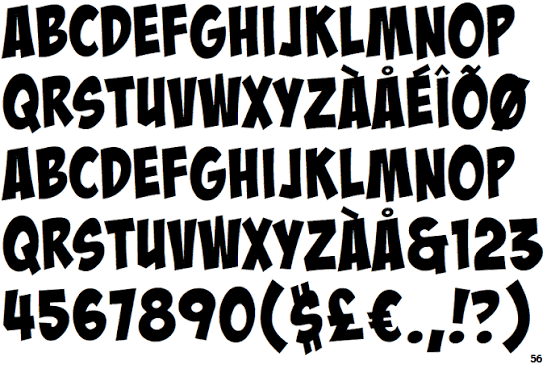
Sở hữu bộ phông chữ Badaboom chuẩn giúp các nhà thiết kế dễ dàng tạo dựng hình ảnh thương hiệu vui tươi, năng động và đầy sức hút. Toàn bộ dữ liệu tại In Viva đã được kiểm soát kỹ thuật kỹ lưỡng, đảm bảo tương thích hoàn hảo với các phần mềm đồ họa chuyên nghiệp hiện nay:
Ký tự đã được rã vector sắc nét, giữ nguyên độ bo tròn và độ đậm của nét vẽ tay đặc thù khi phóng lớn in bạt sân khấu. |
Lưu ý: Badaboom là dòng phông chữ mang phong cách truyện tranh (Comic). Khi sử dụng, bạn hãy kết hợp thêm hiệu ứng viền ngoài (Stroke) và đổ bóng đổ (Drop Shadow) để chữ trông sống động và có chiều sâu hơn.
5 ứng dụng của font Badaboom Việt hóa trong thiết kế và in ấn
Với phong cách chữ truyện tranh mạnh mẽ, vui nhộn và giàu năng lượng, font Badaboom Việt hóa phù hợp với nhiều thiết kế bao bì, tem nhãn và sản phẩm quà tặng hướng đến sự sáng tạo, nổi bật:
- Thiết kế bao bì đồ chơi và bánh kẹo: Badaboom giúp tên sản phẩm trên hộp giấy Ivory, túi giấy hoặc bao bì nhựa trở nên sinh động, dễ thu hút trẻ em và khách hàng trẻ tuổi.
- Sản xuất đồng phục và nón quà tặng: Các câu slogan ngắn sử dụng font Badaboom khi in chuyển nhiệt trên áo thun, nón hoặc vật phẩm sự kiện giúp tạo phong cách năng động, cá tính.
- Thiết kế tem nhãn decal sản phẩm: Font Badaboom phù hợp với sticker, nhãn dán hộp bánh, sản phẩm handmade hoặc thương hiệu trẻ nhờ kiểu chữ khác biệt, dễ tạo điểm nhấn.
- Trang trí voucher và ấn phẩm sự kiện: Khi kết hợp cùng kỹ thuật dập nổi hoặc phủ UV định hình, Badaboom giúp các mẫu voucher, thẻ quà tặng trở nên nổi bật và thu hút hơn.
- Thiết kế banner và poster quảng cáo: Cấu trúc chữ dày, dễ nhận diện giúp Badaboom truyền tải thông điệp khuyến mãi rõ ràng, phù hợp với các chiến dịch cần sự vui nhộn và bắt mắt.
5 lưu ý khi sử dụng font Badaboom Việt hóa
Để font Badaboom Việt hóa giữ được độ sắc nét và hiệu quả thị giác khi ứng dụng vào sản phẩm thực tế, designer cần chú ý:
- Kiểm soát các khoảng trống trong chữ: Badaboom có nhiều chi tiết bo cong và hốc chữ nhỏ. Khi in tem nhãn kích thước nhỏ, cần điều chỉnh kích thước phù hợp để tránh tình trạng mực bị dồn làm mất nét.
- Tối ưu đường Path khi gia công bế nổi: Chuyển đổi font Badaboom sang dạng vector giúp xử lý chính xác các đường cong, đảm bảo logo hoặc tên thương hiệu giữ được độ sắc nét khi dập nổi trên hộp giấy cao cấp.
- Lựa chọn màu sắc phù hợp: Badaboom thường phù hợp với các gam màu nổi bật như đỏ, vàng, cam hoặc xanh. Cần kiểm tra hệ màu CMYK trước khi in để màu sắc giữ được độ tươi sáng.
- Cân chỉnh vùng an toàn khi thiết kế: Khi sử dụng font trên túi giấy, hộp quà hoặc tem nhãn, nên đặt chữ cách mép cắt, đường gấp khoảng cách phù hợp để tránh ảnh hưởng đến bố cục thành phẩm.
- Kiểm tra dấu tiếng Việt trước khi in: Với các tiêu đề lớn, designer nên rà soát lại vị trí dấu thanh để đảm bảo ký tự tiếng Việt hài hòa với kiểu chữ nghiêng, mạnh mẽ đặc trưng của Badaboom.